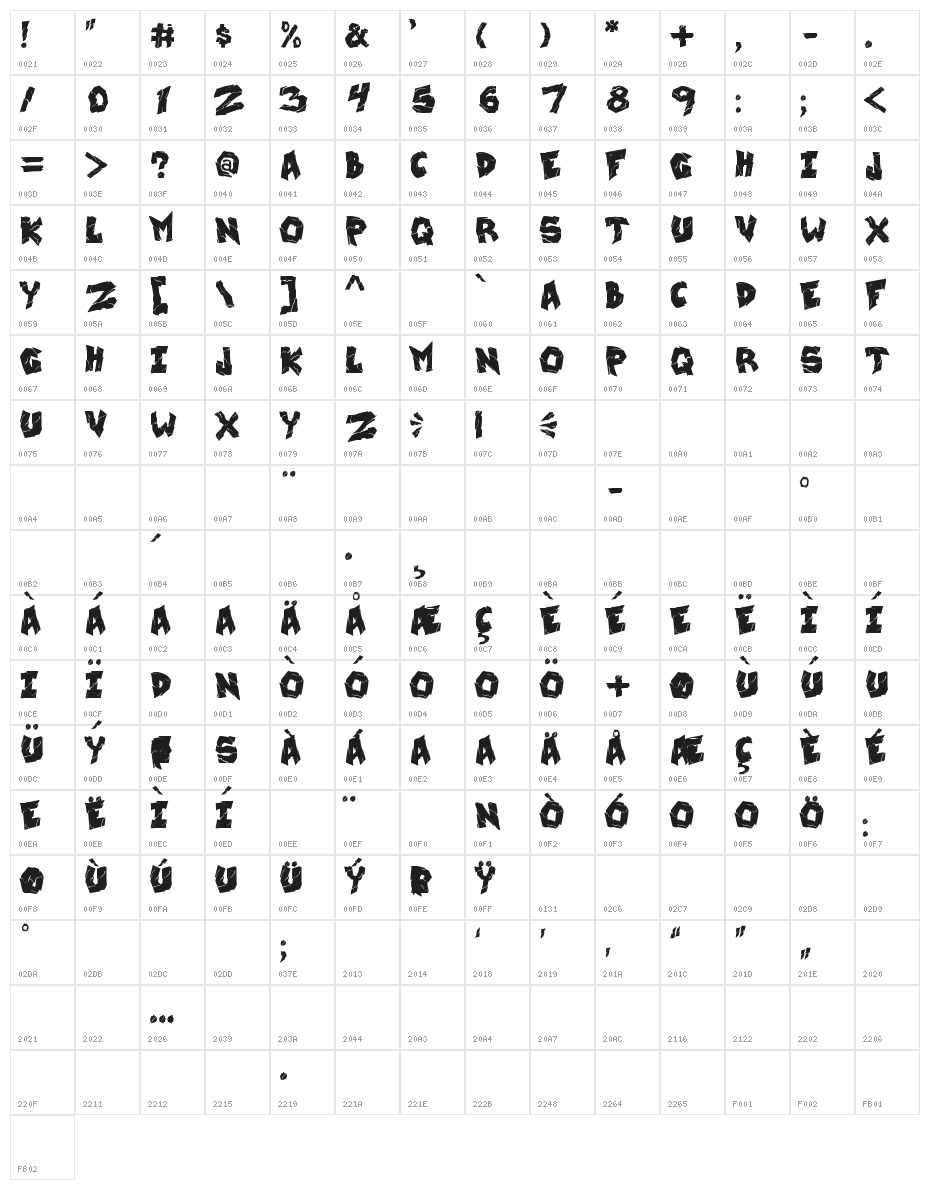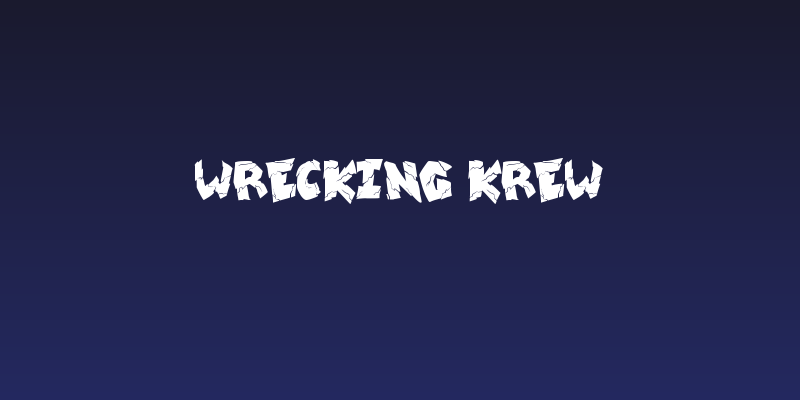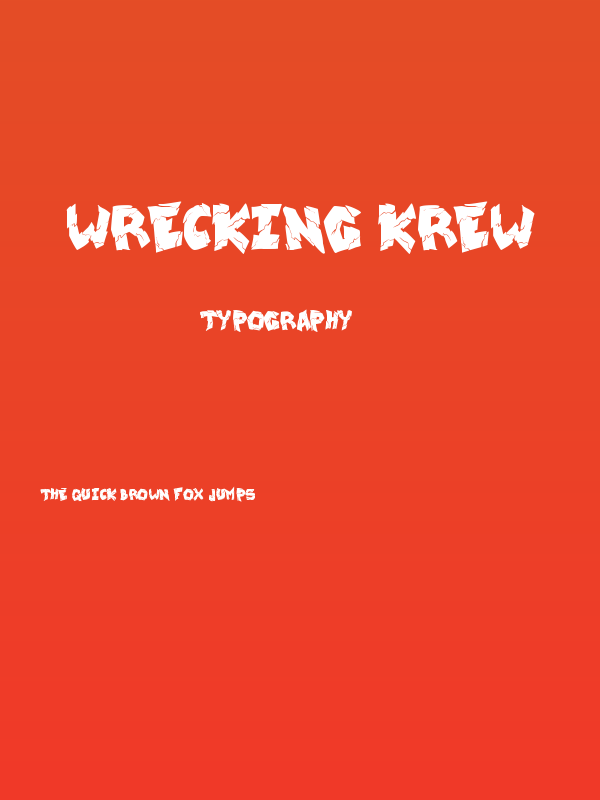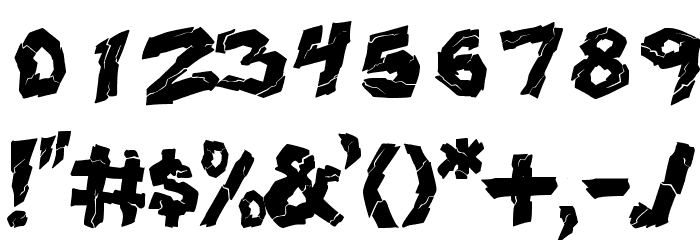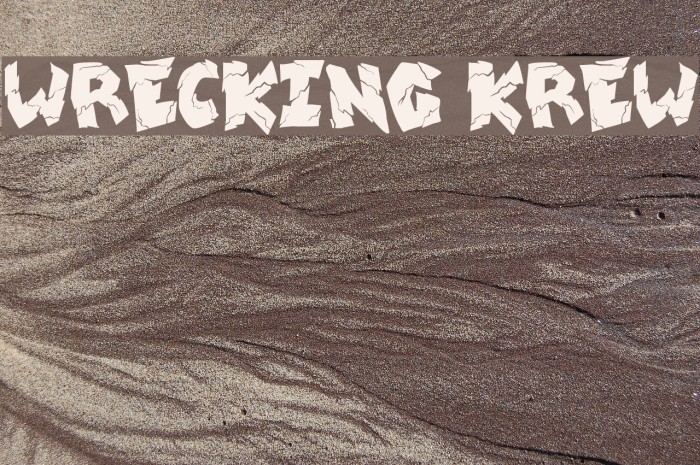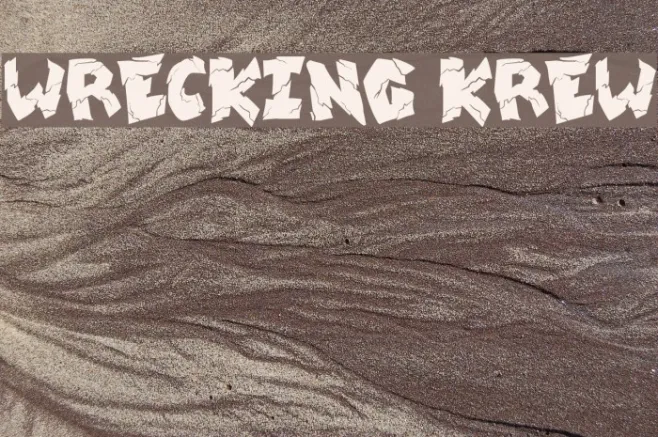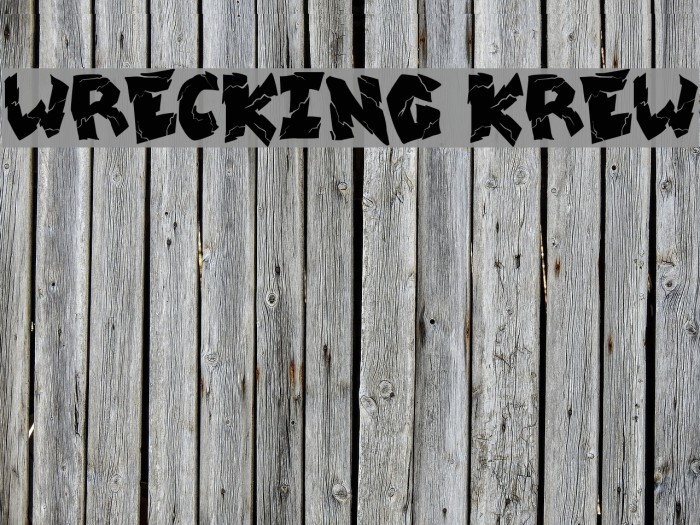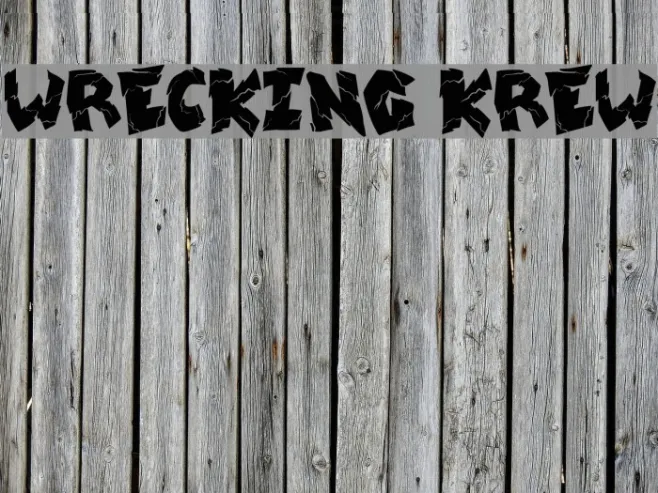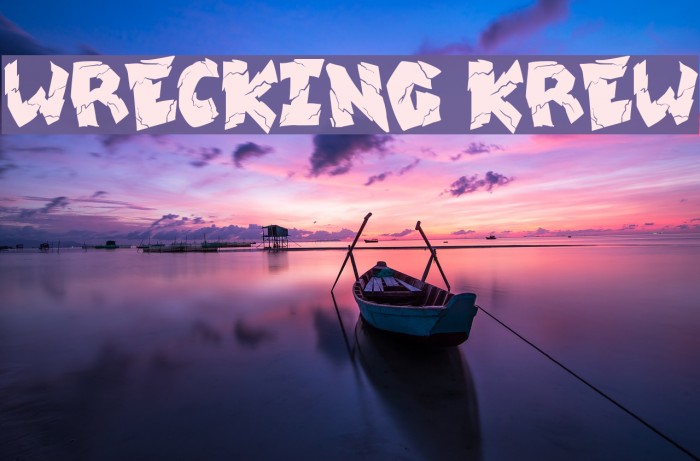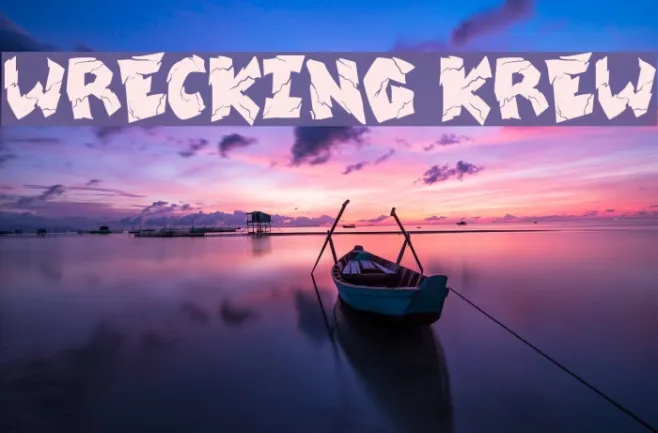
wrecking krew Font
✎ Distorted Eroded
| Categorías | Distorted Eroded |
| Estilo general | Modern, Edgy |
| Proyectos propuestos | Ideal for music album covers, event posters, video game titles, and any project needing a bold, edgy aesthetic. |